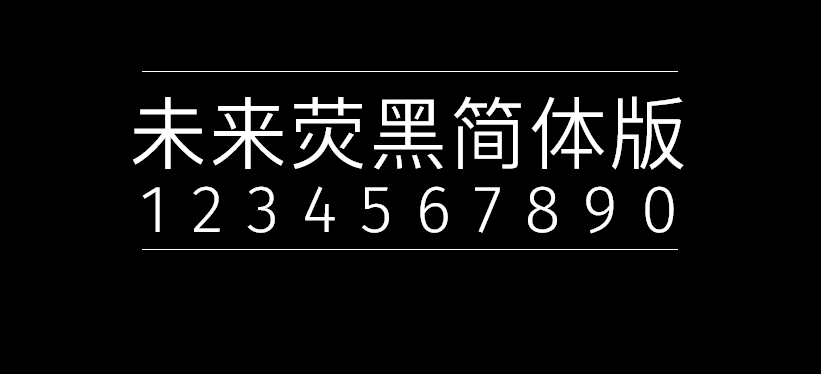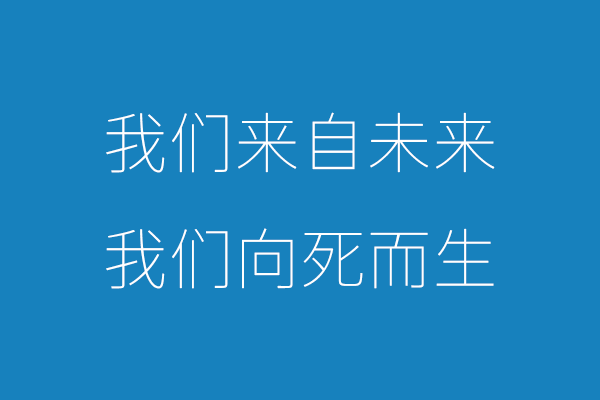
未来荧黑简体版
未来荧黑(Glow Sans SC)是一个基于思源黑体、Fira Sans和Raleway的开源字体项目,支持简体中文、繁体中文与日文,作者是Celestial Phineas。
免费商用字体「未来荧黑」开放下载!5种字宽+9种字重超好用!在思源黑体的7种字重基础上,扩展为9种字重,并增加了5种字体宽度,全家族共包含44款字体。
与思源黑体有何不同?
相比于思源黑体,未来荧黑的造型更加简明现代,版面效果清新轻快。未来荧黑的中宫与字面更加收敛,重心在字重之间经过了重新配置;笔画细节上处理得更加干练,简洁而平直化。